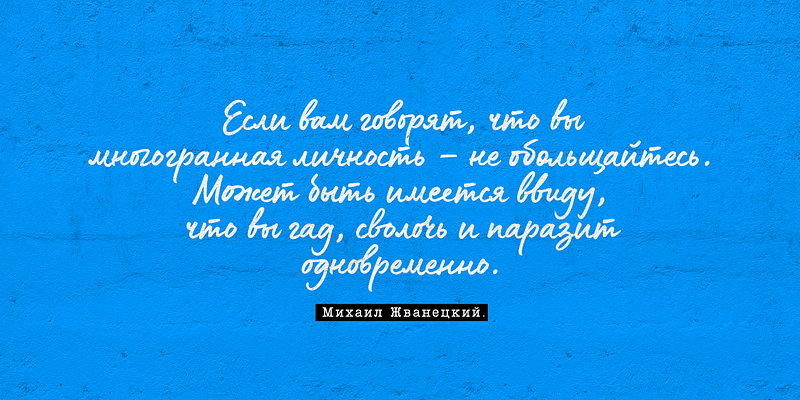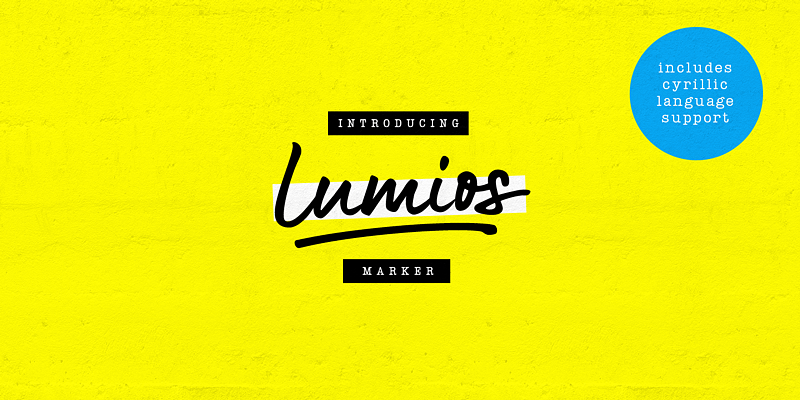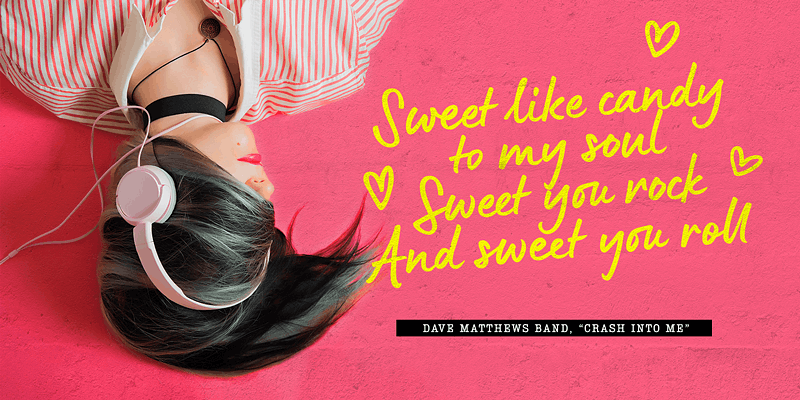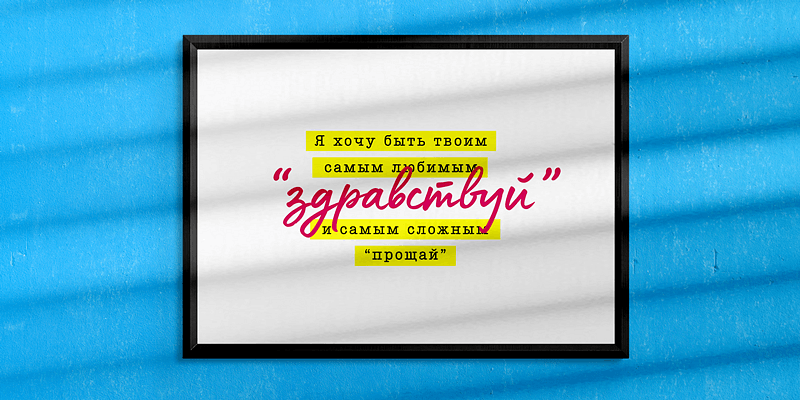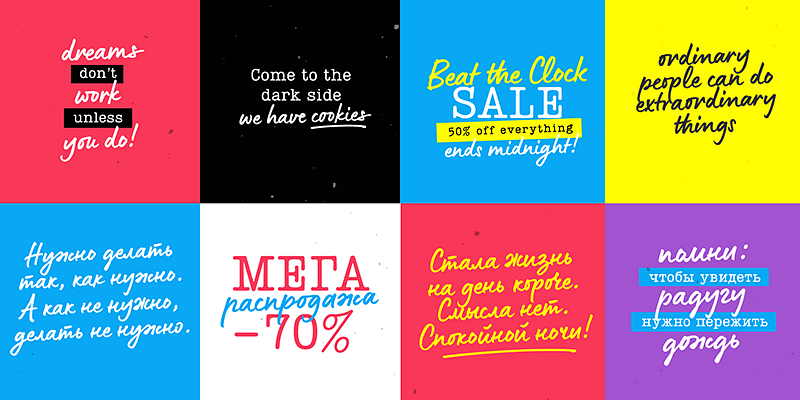
My Creative Land ospita i caratteri tipografici meravigliosamente realizzati a mano di Elena Genova. Con una dedizione incrollabile all’arte delle lettere, i volti trascendono l’ordinario e trasmettono emozione, profondità e unicità nel design. Ogni famiglia è realizzata a mano con cura e spesso trae ispirazione diretta dalla bellezza che si trova nella calligrafia e nella scrittura. I designer più esigenti sapranno che My Creative Land ha font pronti a infondere un certo je ne sais quoi per amplificare le loro idee sopra il resto.